NEXON 무료폰트
넥슨 Lv.1 고딕
넥슨 Lv.1 고딕은 넥슨이 추구하는 젊음, 즐거운 세상에 전하는 서체.
가독성 좋은 본문용 글꼴로서 다양한 게임들을 아우르며 모바일, 웹, 인쇄 등 다양한 매체 사용에 무리 없도록 제작.
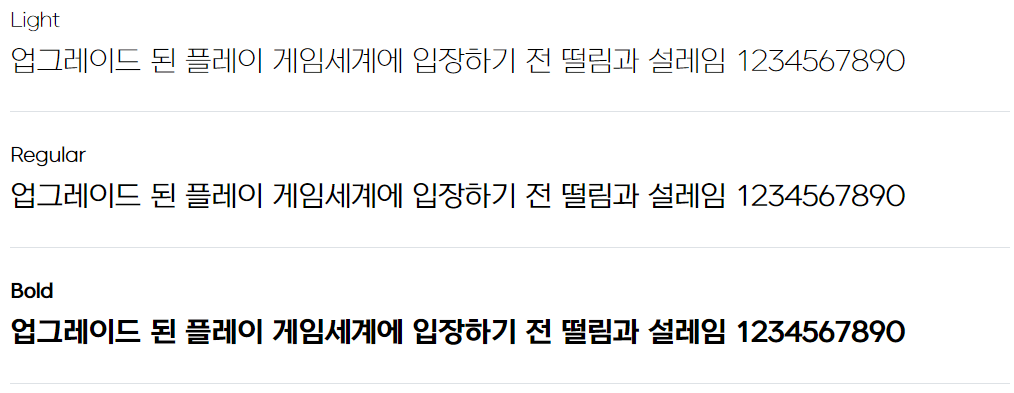
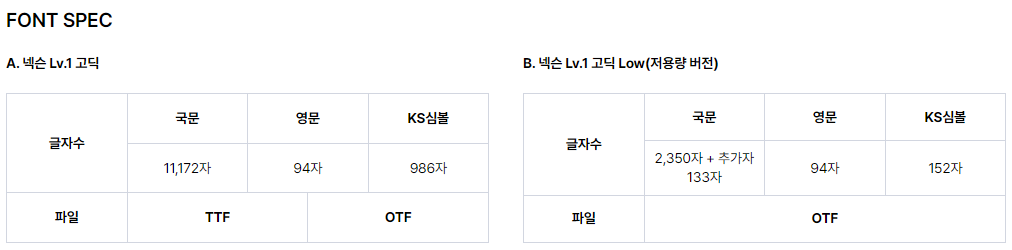
넥슨 Lv.2 고딕
다양한 분야에서 두루 사용할 수 있는 넥슨 Lv.2 고딕 서체입니다.
온/오프라인 적용에 구애받지 않고, 젊고 귀여운 넥슨 Lv.1 고딕보다 성숙하고 어른스러운 느낌의 서체.
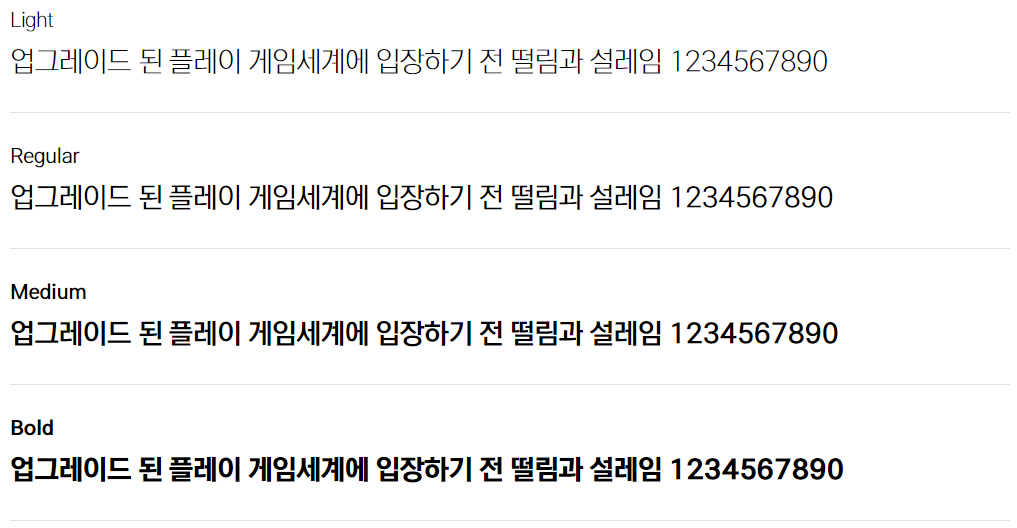
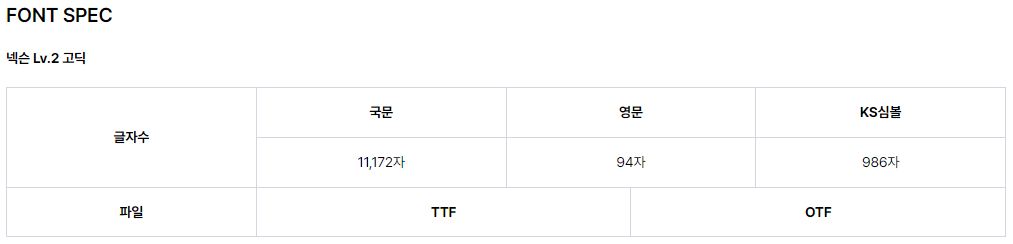
넥슨 배찌체
넥슨 배찌체는 2019년 공모전을 통해 제작된 서체입니다.
배찌를 사랑해 주시고 특징을 잘 이해하고 계신 유저분들의 참여로 완성된 서체.
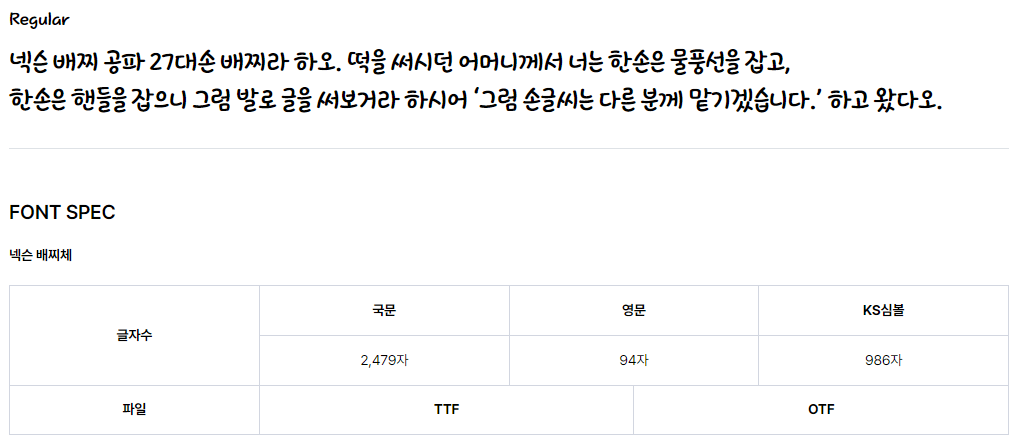
넥슨 풋볼 고딕
넥슨 풋볼 고딕은 축구 경기의 역동적이며 박진감 넘치는 느낌을 토대로 제작된 폰트입니다.
긴장감 있는 폰트를 표현하기 위해 장평을 넓히고 글자의 간격은 좁혀 글자에 안정감을 주었습니다.
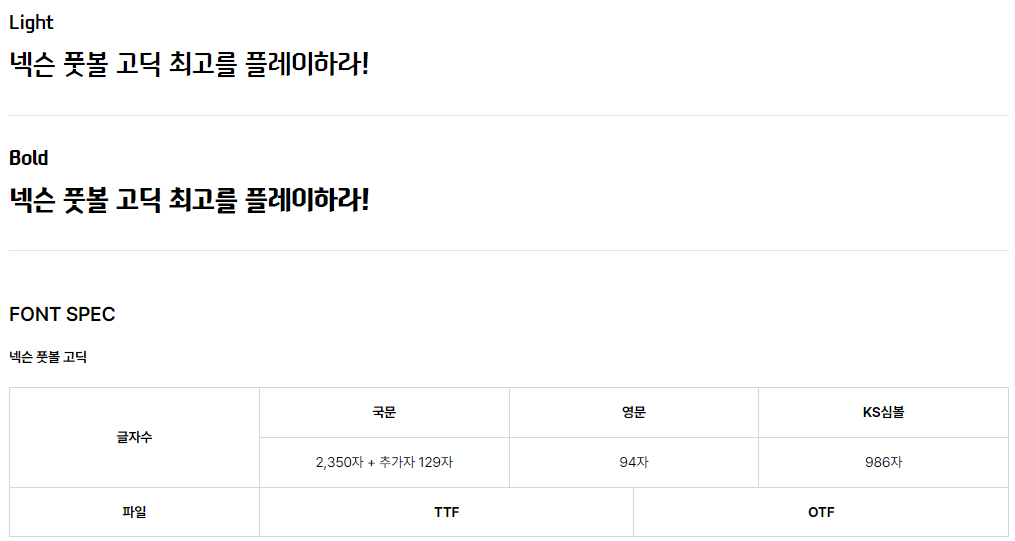
넥슨 메이플스토리
메이플스토리 서체는 귀엽고 발랄한 캐릭터와 재미있고 유쾌한 게임 분위기를 반영하여 제작하였습니다.
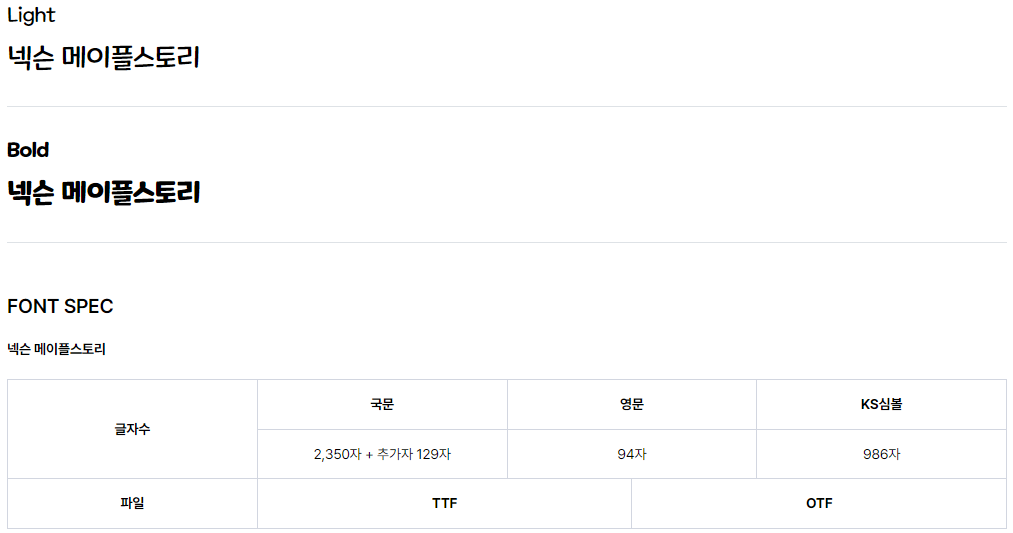
던파 비트비트 v2
비트비트체는 ‘비트비트 8비트’에서 영감을 얻어, 도트/픽셀 아트와 가장 잘 어울리도록 디자인된 ‘제목용 서체’입니다.
저해상도에 최적화된 비트맵 폰트를 고해상도에도 비트맵 폰트의 특징을 그대로 표현될 수 있게 계단 형태의 디자인을 하나의 질감으로 표현하여 제작하였습니다.
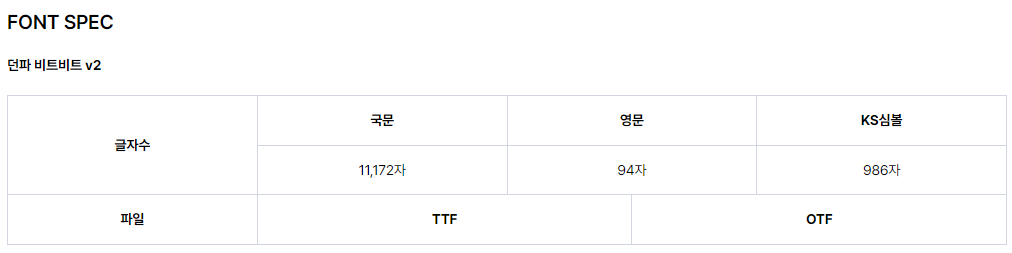
던파 연단된 칼날
거침없이 돌아가는 톱니바퀴를 모티브 하여, 운명의 굴레 속에서 ‘연단된 칼날’의 강한 저항력과 의지를 담고 있습니다.
또한, 그래픽요소가 들어간 자소와 세리프를 통하여 던전 앤 파이터만의 통쾌한 타격감과 액션감을 함께 느낄 수 있습니다.
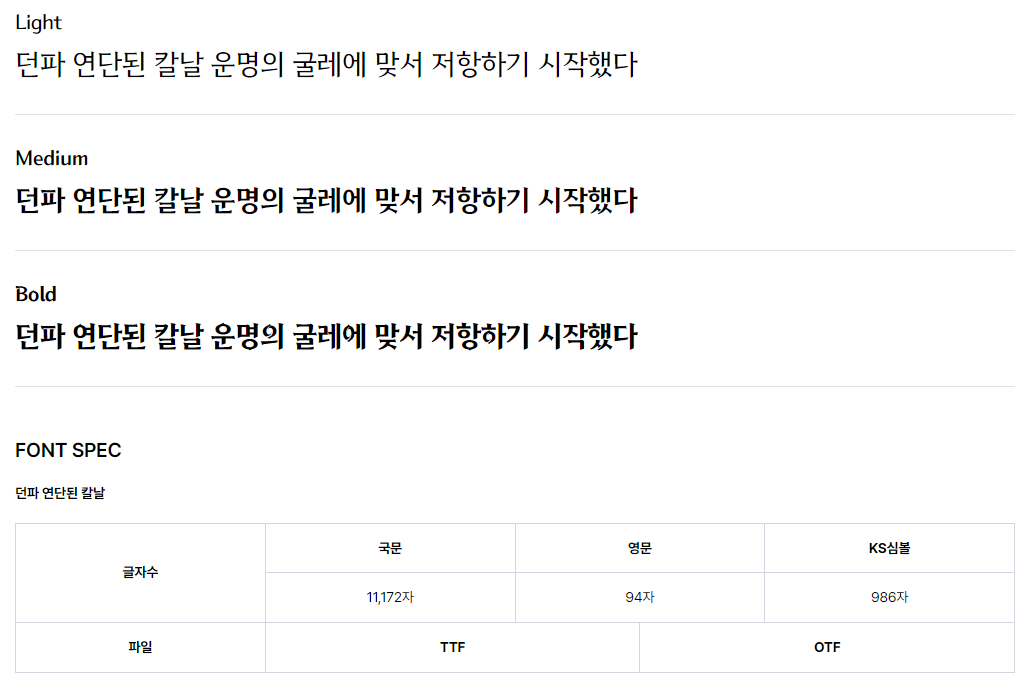
넥슨 워헤이븐체
워메이븐체는 근접 무기들이 맞부딪히는 전장에서 주는 단단하고 강한 분위기를 살려 디자인되었습니다.
고딕 서체의 단단한 골격으로 강한 인상을 살리고, 브래킷이 있는 웨지 세리프와 각진 획 꺾임 포인트를 엿볼 수 있습니다.
넥슨 카트 고딕
대표적인 레이싱 게임인 카트라이더: 드리프트는 사용자의 폭이 넓고 다양하여 친근함, 밝고 경쾌한 게임의 특성, 드리프트의 특장점을 서체의 형태적 느낌으로 표현하고자 하였습니다.
마비옛체
마비옛체는 마비노기의 공식폰트로 마비옛체를 통해 에린의 발랄하고 평화로운 분위기에 녹아들었습니다.
오랫동안 밀레시안과 에린을 이어주는 소중한 소통 창구였던 마비옛체. 마비노기의 상징인 서체.
원스토어 모바일고딕 본문체
모바일에 최적화된 본문용 서체. 모던하면서도 편안한 인상의 자소 디자인 환경과 최적화된 그 줄을 설정.
원스토어 모바일고딕 제목체
베이직한 힘으로 시선을 잡아끄는 제목용 서체. 안정적이고 단단한 글줄과 부드러운 힘을 가진 자소 디자인을 가지고 있다.
원스토어 모바일고딕 POP 체
원스토어만의 성격이 담긴 생동감 있는 손글씨 서체. 글자에 생기를 불어넣는 리드미컬한 라인과 요소를 담음.
컴투스 홀딩스 빛의 계승자
컴투스 홀딩스 생존자폰트